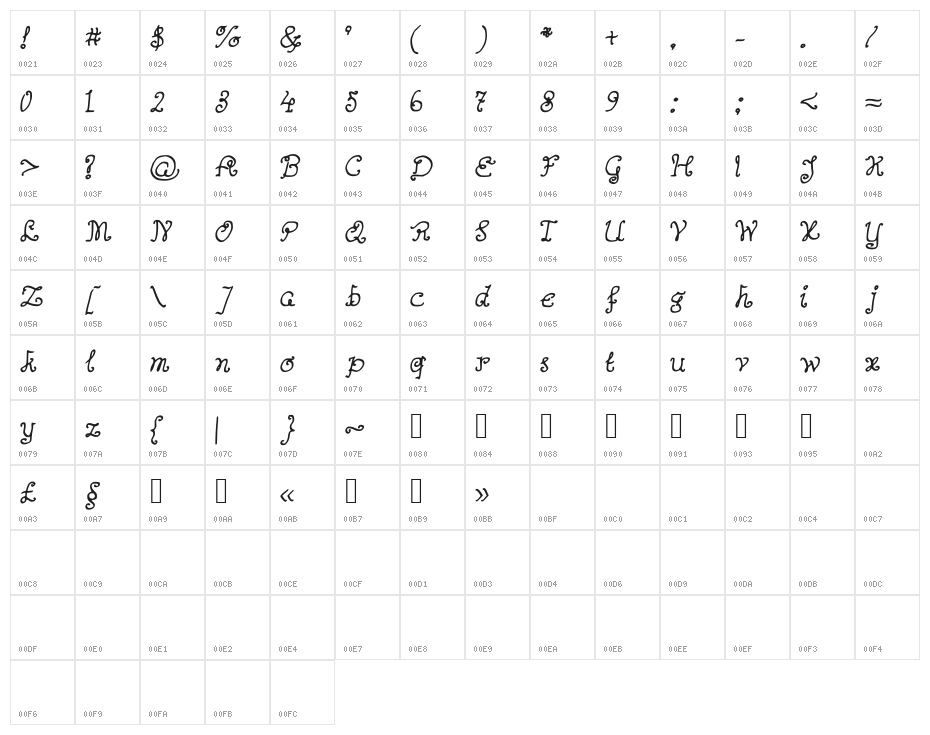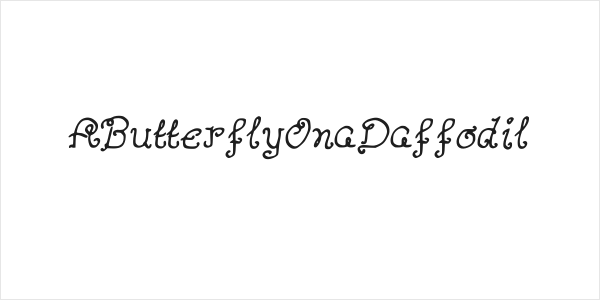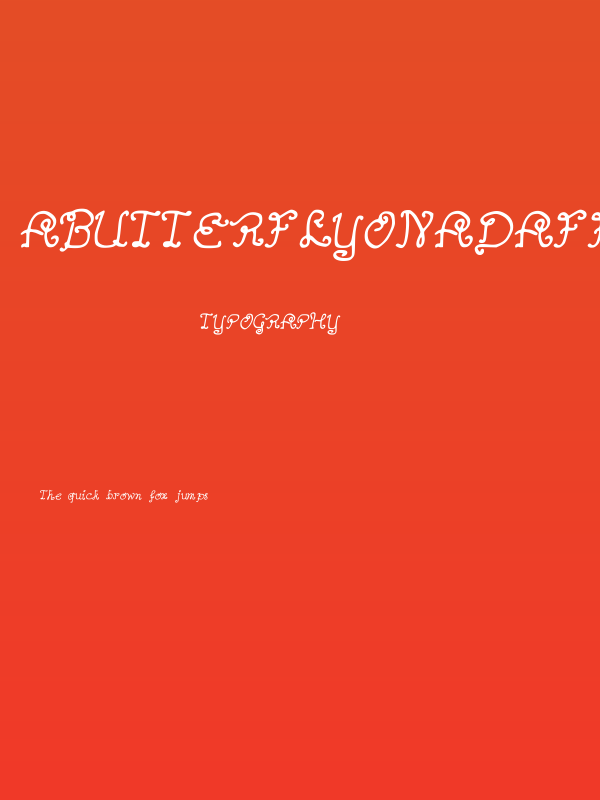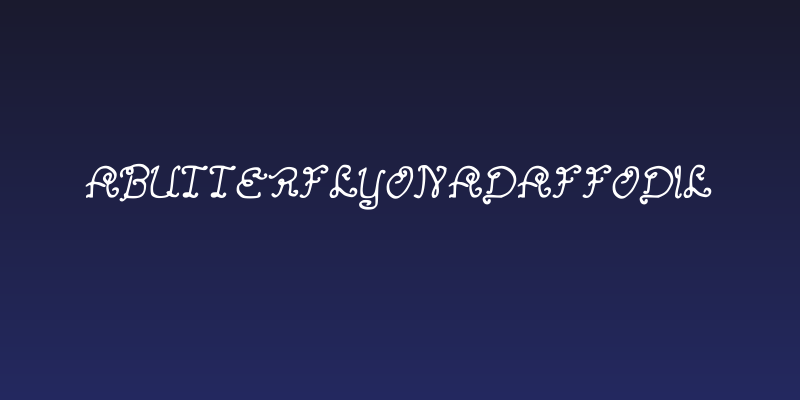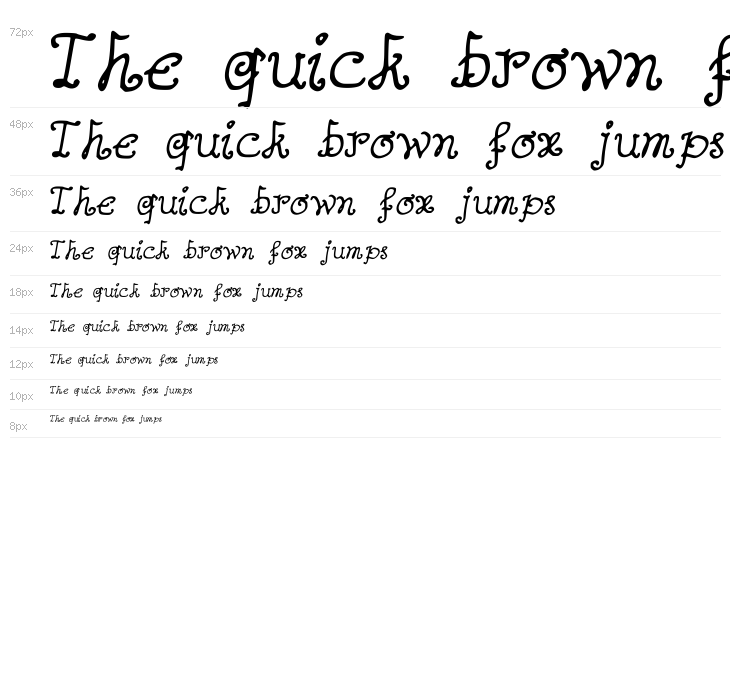
AButterflyOnaDaffodil Font
✎ Curly
| Anwendungsfall | Headlines, Logos, Artistic projects |
| Vorgeschlagene Projekte | Ideal for invitations, greeting cards, artistic posters, and branding projects that require a decorative and unique touch. |